Как спланировать набор знаков для рукописной расшифровки интервью
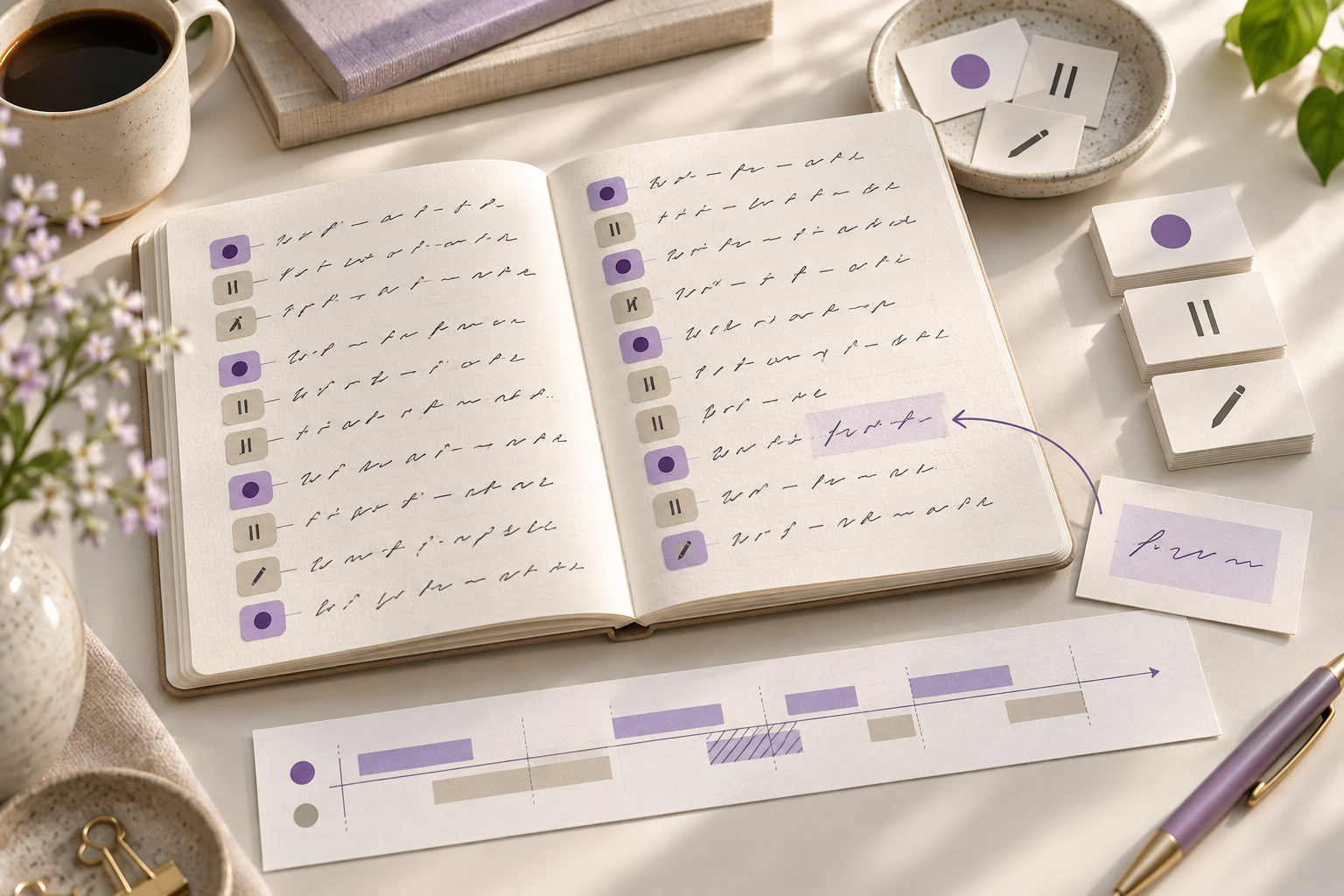
Рукописный шрифт для расшифровки интервью должен поддерживать не только обычный текст, но и условные обозначения: имена говорящих, временные метки, паузы, обрывы фраз и неразборчивые места. Чтобы не рисовать лишнее и не обнаружить пропуск в конце, сначала соберите реальные фрагменты будущих расшифровок, составьте по ним реестр знаков и расставьте приоритеты по частоте и смысловой важности.
Сначала определите, что именно вы называете расшифровкой
В разных проектах словом «расшифровка» называют разные результаты: дословную запись каждого слова, очищенный текст без оговорок, краткое конспектирование или стенограмму для исследования. От выбранного формата зависит набор символов. Если редактор удаляет повторы и междометия, знак повтора может не понадобиться; если анализируется ход разговора, пауза, перебивание или незаконченная фраза иногда несут смысл и должны сохраняться.
Запишите назначение текста, тип читателя и способ дальнейшей обработки. Например: «полуструктурированное интервью для качественного исследования; текст читают два кодировщика; заметки и метки должны оставаться различимы при печати». Это короткое описание станет фильтром для каждого кандидата в набор: нужен ли знак самому тексту, помогает ли он читателю или его можно безопасно хранить обычной пунктуацией.
Также заранее договоритесь о правилах разметки. Не существует одной обязательной для всех бытовых и исследовательских транскриптов системы символов. Внутри проекта важно, чтобы один знак всегда означал одно и то же, а участники команды одинаково его использовали. Шрифт не должен подменять редакционную конвенцию: сначала задайте значение, затем решайте, нужен ли для него отдельный глиф.
Соберите короткие реальные образцы
Не составляйте список символов по памяти. Возьмите обезличенные куски, похожие на будущие материалы: спокойный ответ, короткое подтверждение, длинную реплику, перебивание, паузу, самопоправку, цитату и участок с отметкой времени. Достаточно нескольких страниц разного типа, если они отражают реальную практику. Удалите имена, контакты и другие сведения, по которым можно узнать собеседника.
Если готовых текстов ещё нет, создайте тестовые отрывки по сценариям интервью, но пометьте их как макеты. Не добавляйте редкие ситуации только потому, что они выглядят выразительно. Например, один пример с тремя говорящими полезен, если групповое интервью действительно будет частью проекта; для одиночных интервью это может быть необязательный крайний случай.
Разметьте каждый фрагмент прямо в рабочем тексте: кто говорит, где начинается новая реплика, какие паузы фиксируются, как отмечаются наложения речи, что происходит с неполным словом, как выглядит неразборчивая часть. Затем посчитайте не только отдельные символы, но и повторяющиеся комбинации: И:, М:, (пауза), [смех], 12:34. Для планирования важна вся связка, потому что знак может быть технически доступен, но плохо различим в употреблении.
Разделите набор на четыре слоя
Так легче оценить, что нужно нарисовать обязательно, а что можно отложить до проверки первых страниц.
- **Базовый текст.** Кириллица для основных реплик, прописные и строчные, пробел, стандартные цифры и знаки препинания. Добавьте латиницу, только если имена, аббревиатуры или термины регулярно встречаются в материале.
- **Организация диалога.** Двоеточие после метки говорящего, тире или другой принятый маркер начала реплики, скобки либо квадратные скобки для редакторских помет, кавычки для цитаты. Выберите одну систему, чтобы не смешивать варианты без причины.
- **События речи.** Знаки или сочетания для паузы, смеха, вздоха, перебивания, одновременной речи, обрыва и неразборчивого фрагмента. Часть таких обозначений будет словами в скобках, поэтому отдельные «иконки» обычно не нужны.
- **Рабочая навигация.** Метки времени, номера говорящих, номера вопросов, теги темы или поля для кодирования. Если классификация делается в таблице или программе, не включайте все её маркеры в шрифт без практической причины.
Смысл такого деления не в том, чтобы создать четыре начертания, а в том, чтобы обнаружить зависимости. Например, метка УЧАСТНИК 2: требует не только букв, но и цифры, пробела и двоеточия; временной код 08:17 — цифр и устойчивой формы двоеточия. Проверять нужно связки, а не только наличие символов в списке.
Определите правила для сложных случаев
Для каждого явления выберите обозначение и запишите его в небольшую таблицу конвенций. Она одновременно служит спецификацией набора знаков.
- Метка говорящего — `И:` перед каждой репликой. Проверить: Заглавная буква, двоеточие, одинаковая ширина меток.
- Короткая пауза — `(пауза)` только если она значима. Проверить: Скобки, кириллица, пробелы.
- Неуверенность в слове — `[возможно: поезд]`. Проверить: Квадратные скобки, двоеточие.
- Обрыв слова — `по-` или многоточие по принятому правилу. Проверить: Дефис и многоточие не должны сливаться.